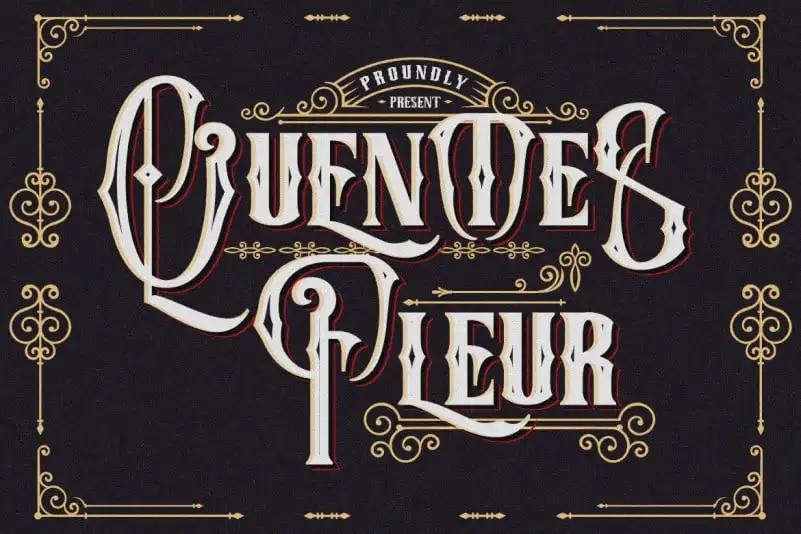
A Quentes Fleur Display Font é uma elegante fonte vintage ideal para rótulos e design gráfico, criada pelo designer gráfico FallenGraphic Studio. Este fonte apresenta uma seleção diversificada de tipografias com alternativas carismáticas que mantêm um olhar coeso e elegante ao longo do design. Perfeito para criar rótulos distintivos ou estilos de design retro, a Quentes Fleur é uma escolha ideal para quem procura fontes vintage modernizadas sem perder o charme nostálgico. Ideal tanto para aplicar em projetos de marketing quanto em criações artísticas que valorizam o estilo e o bom gosto no design gráfico atual.